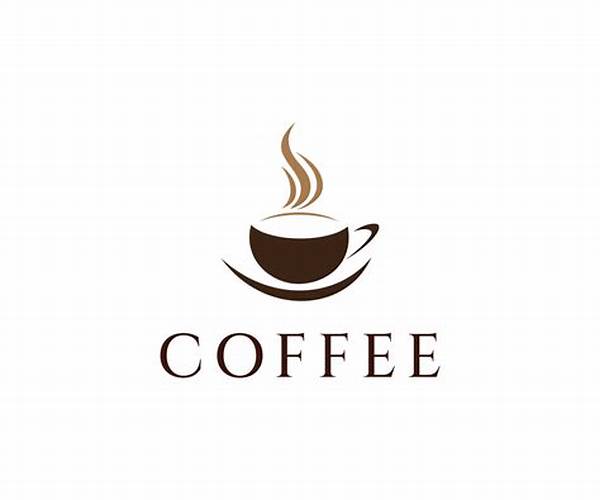
Hai para pecinta kopi dan penikmat desain! Apakah kalian pernah berpikir betapa pentingnya sebuah logo untuk sebuah kafe? Logo adalah wajah pertama yang dilihat oleh pelanggan ketika menjalankan bisnis, apalagi di industri yang sangat visual seperti kafe. Maka dari itu, menggunakan font unik untuk logo kafe bisa jadi pembeda yang menarik bagi bisnis Anda. Mari kita bahas lebih lanjut kenapa font bisa menjadi elemen kunci dalam logo kafe.
Mengapa Font Unik untuk Logo Kafe Penting?
Memilih font unik untuk logo kafe bukan hanya soal estetika, tetapi juga soal identitas dari kafe itu sendiri. Dayakanlah font yang tidak terlalu mirip dengan yang lain agar pelanggan bisa dengan mudah mengenali logo Anda. Misalnya, ketika kita berpikir tentang brand-brand besar, kita seringkali teringat akan bentuk huruf yang digunakan dalam logonya. Dengan menggunakan font yang tepat, sebuah logo bisa menyampaikan pesan yang ingin ditunjukkan oleh kafe Anda.
Font juga berperan dalam menciptakan suasana yang diinginkan. Sebagai contoh, jika Anda mengelola kafe dengan tema retro, maka memilih font dengan gaya vintage bisa sangat efektif. Dengan begitu, setiap elemen dari font unik untuk logo kafe Anda akan selaras dengan konsep keseluruhan dari tempat tersebut, menciptakan harmoni dan menarik perhatian calon pelanggan.
Selain estetika, uniknya sebuah font bisa menambah keaslian pada brand Anda. Di dunia yang dipenuhi oleh saingan, karakteristik yang khas bisa membantu kafe Anda menonjol. Seiring waktu, font unik yang terus dikenali akan memberi dampak pada loyalitas pelanggan. Jadi, tidak hanya sekadar memilih font karena tren semata, tetapi font tersebut haruslah representatif dan autentik bagi brand kafe.
Tips Memilih Font Unik untuk Logo Kafe
1. Pahami Tema Kafe Anda: Jika kafe Anda memiliki tema tertentu, pilihlah font yang selaras dengan tema tersebut. Font unik untuk logo kafe harus dapat mencerminkan suasana yang ingin Anda sampaikan.
2. Kepastian Mudah Dibaca: Font yang terlihat keren memang menarik, tapi pastikan tetap mudah dibaca. Tidak ada gunanya memiliki font unik untuk logo kafe jika pelanggan tidak bisa membacanya dengan jelas.
4. Eksperimen dengan Kombinasi: Jangan takut untuk mencoba berbagai kombinasi font. Kadang, kombinasi dua jenis font yang berbeda dapat menciptakan efek visual yang menarik.
5. Minta Umpan Balik: Setelah memilih beberapa opsi, mintalah pendapat orang lain. Perspektif yang berbeda bisa memberikan wawasan berharga mengenai font unik untuk logo kafe Anda.
Manfaat dari Font Unik untuk Logo Kafe
Memilih font unik untuk logo kafe tentunya membawa banyak manfaat. Pertama, font yang unik dan menarik dapat langsung memikat hati pelanggan. Saat seseorang melihat logo Anda, font tersebut bisa jadi elemen pertama yang menarik perhatian, menggugah rasa penasaran mereka untuk mengunjungi kafe Anda.
Kemudian, font unik bisa menjadi pembeda yang jelas antara kafe Anda dengan yang lain. Di zaman yang serba visual ini, sangat penting untuk memiliki identitas yang kuat dan berbeda. Logo yang dilengkapi dengan font yang unik dapat menjadi alat pemasaran yang efisien, memberikan kesan yang tak terlupakan bagi pelanggan.
Cara Mendapatkan Font Unik untuk Logo Kafe
Penting juga untuk mempertimbangkan untuk bekerja sama dengan desainer grafis. Mereka dapat membuat font kustom khusus untuk logo Anda, sesuatu yang benar-benar unik dan tidak ada di tempat lain. Dengan kolaborasi ini, Anda bisa mendapatkan sebuah font yang benar-benar mewakili visi dan misi dari kafe Anda.
Jangan lupa juga untuk mempertimbangkan keluwesan penggunaannya. Logo dengan font yang menarik harus mampu tampil di berbagai media, baik itu di papan nama, kartu nama, atau bahkan merchandise kafe Anda. Pilihlah font unik untuk logo kafe yang pas dan sesuai di berbagai tempat.
Menghindari Kesalahan dalam Memilih Font Unik untuk Logo Kafe
Ada kesalahan umum yang sering terjadi ketika memilih font unik untuk logo kafe, dan menyadarinya sejak awal bisa membantu Anda. Misalnya, jangan hanya mengikuti tren semata. Tren bisa berubah, tetapi identitas brand Anda seharusnya stabil. Logo yang bergantung pada tren dapat menjadi usang dalam waktu singkat.
Selanjutnya, jangan abaikan pentingnya konsistensi. Setelah Anda memilih font untuk logo, tetaplah konsisten dalam penggunaannya di semua materi promosi dan branding. Konsistensi ini dapat meningkatkan pengenalan brand dan memperkuat identitas kafe Anda.
Mengapa harus berhenti pada yang biasa saat Anda bisa menonjol dengan yang unik? Percayalah, font yang tepat dapat menjadikan sebuah logo lebih dari sekadar simbol visual; ia berbicara banyak tentang karakter dan semangat kafe. Jadi, jangan ragu untuk berinvestasi waktu dan usaha dalam memilih font unik untuk logo kafe Anda. Dengan begitu, Anda telah membangun langkah awal yang kuat untuk meraih kesuksesan dalam bisnis kafe Anda.